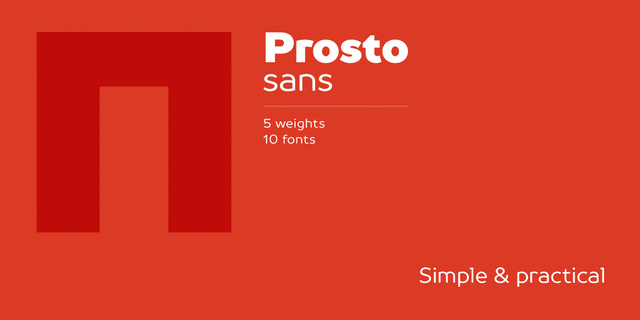
Просто Санс – это шрифт на все случаи жизни! Вы можете использовать его практически везде. Современные открытые гротесковые формы и классическая формула: Тонкий, Светлый, Нормальный, Жирный, Сверхжирный + наклонные начертания. Просто Санс поможет вам в работе над любым проектом. Шрифт Разработан Иваном Гладких в студии TypeType в 2014 году.
минималистичный, четкий, деликатный, чистый, легкий, прохладный, свежий, модный, тонкий, современный, лаконичный, ясный, ровный, понятный, качественный, городской, логичный, точный, глобализированный, глобалистичный, интимный, хрупкий, проволочный, худой, простой, твердый, доступный, элементарный, правильный, строгий, серьезный, устойчивый, статичный, стабильный, самостоятельный, ответственный, западный, деловой, холодный, спокойный, комфортный, безразличный, равнодушный, вежливый, значительный, обязательный, солидный, сильный, убедительный, важный, мотивирующий, надежный, тяжелый, урбанистический, грубый, заметный, яркий, активный, броский